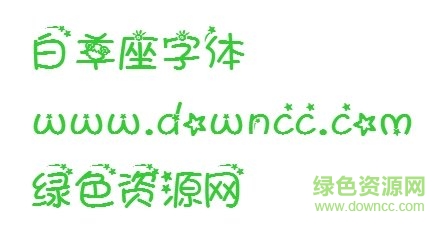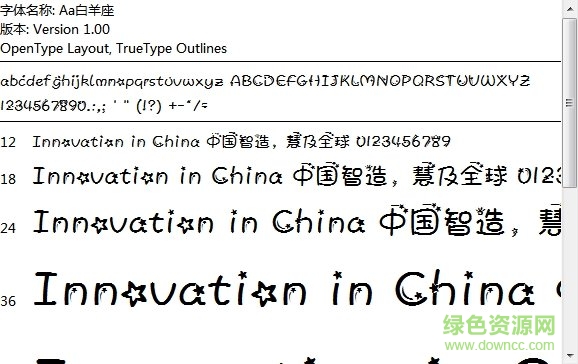
白羊座字體是aa字庫(kù)推出的一款星座字體,字里行間充滿了各式各樣的點(diǎn)綴,講文字的某個(gè)部首也美化成了可愛(ài)的圖案,給用戶更加愉悅的視覺(jué)體驗(yàn),綠色資源網(wǎng)歡迎大家下載使用!
白羊座字體是以《Aa胖丫兒》為打底字,添加了流星和羊頭等元素來(lái)體現(xiàn)白羊的特性,是十二星座特色美化字之一。
白羊座字體專為白羊座的寶寶們打造的個(gè)性卡通字體,豐富圖案和特色點(diǎn)綴,讓文字更顯生活活潑,運(yùn)用在平面設(shè)計(jì)、藝術(shù)設(shè)計(jì)、包裝設(shè)計(jì)等領(lǐng)域均可。